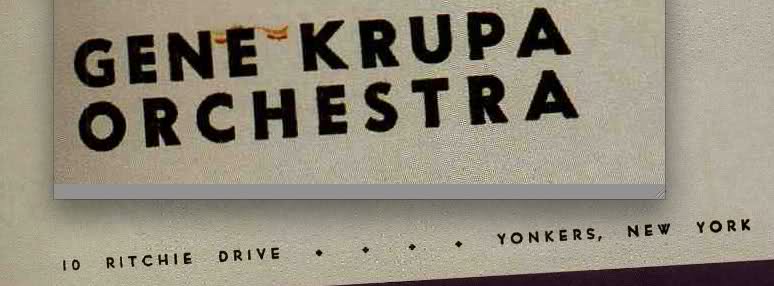
alte US schrift - bitte um info
ne, diesen part habe ich noch ...
Sieht ein bisschen aus wie die Bernhard Gothic von Lucian Bernhard (1929-30):
Die fette sieht ähnlich aus wie die Metro von William Addison Dwiggins (1936):
Aber die Schriften im Buch sind jeweils stumpf, die oben angegebenen sind spitz. :?
ne, diesen part habe ich noch ...
Sieht ein bisschen aus wie die Bernhard Gothic von Lucian Bernhard (1929-30):
nice catch. :rockon: die fette ist allerdings tricky.